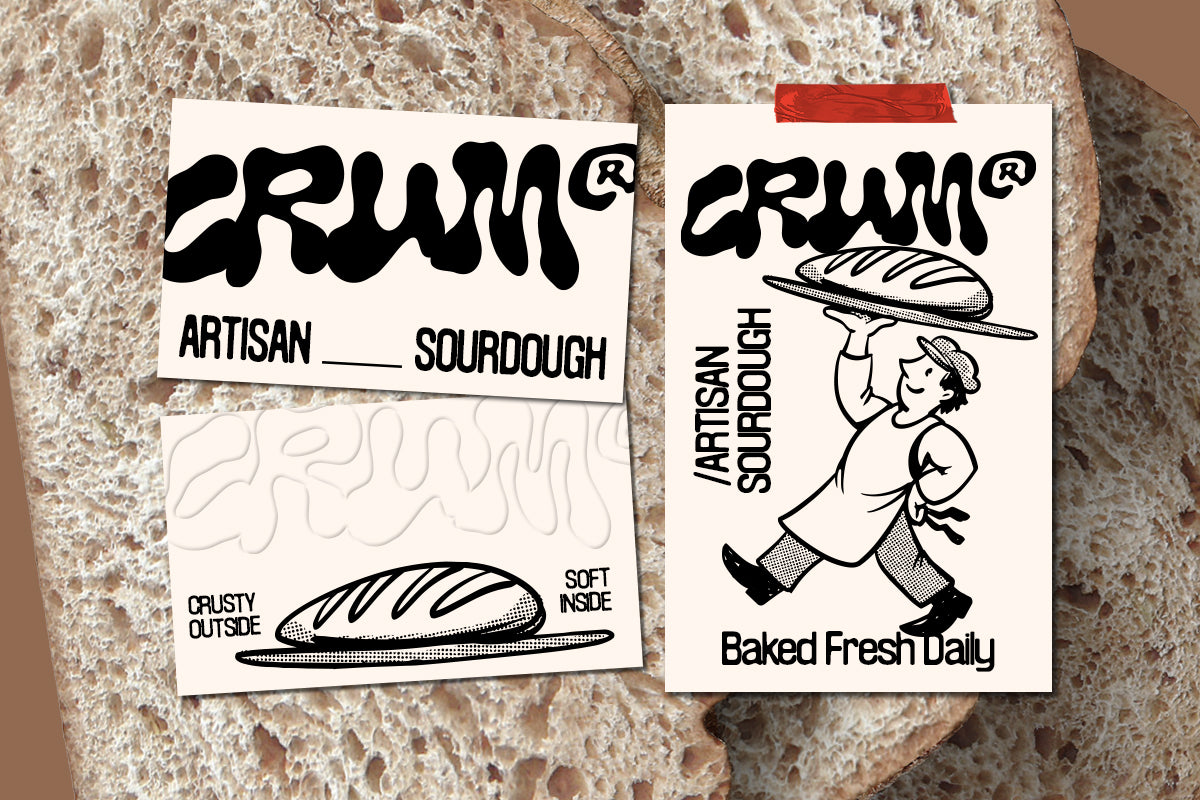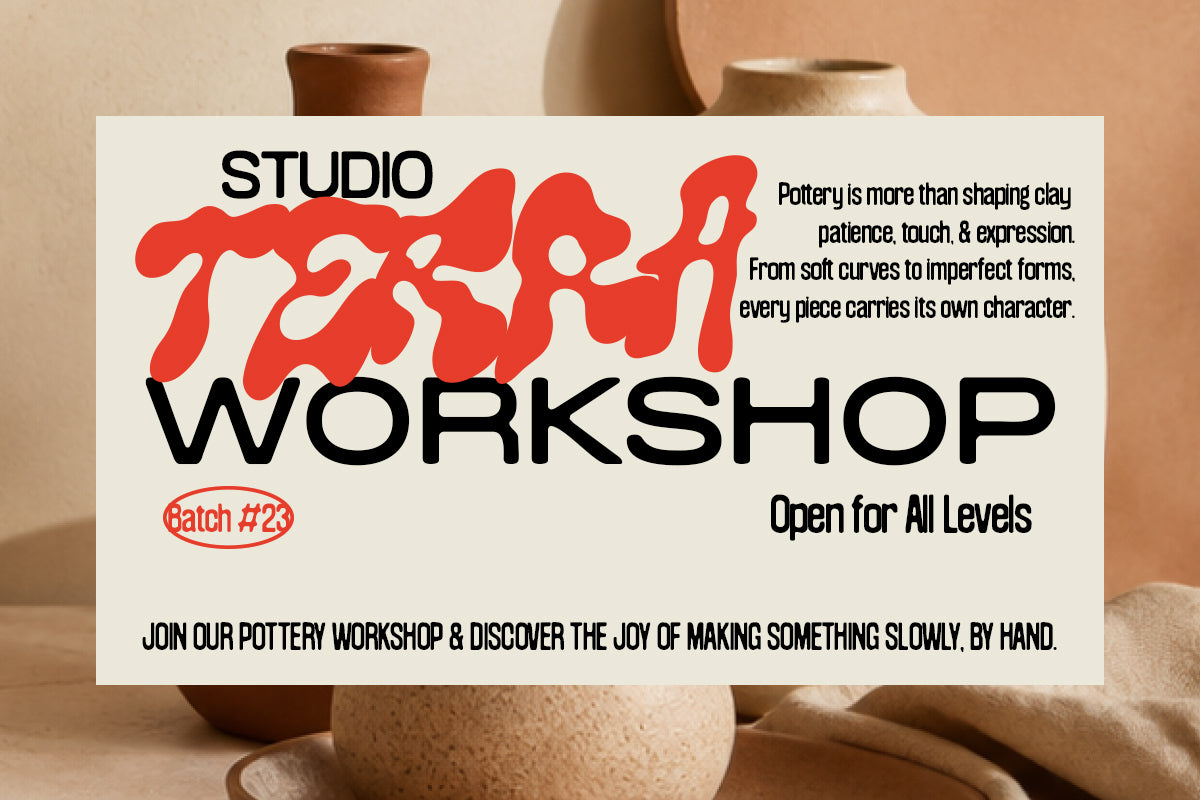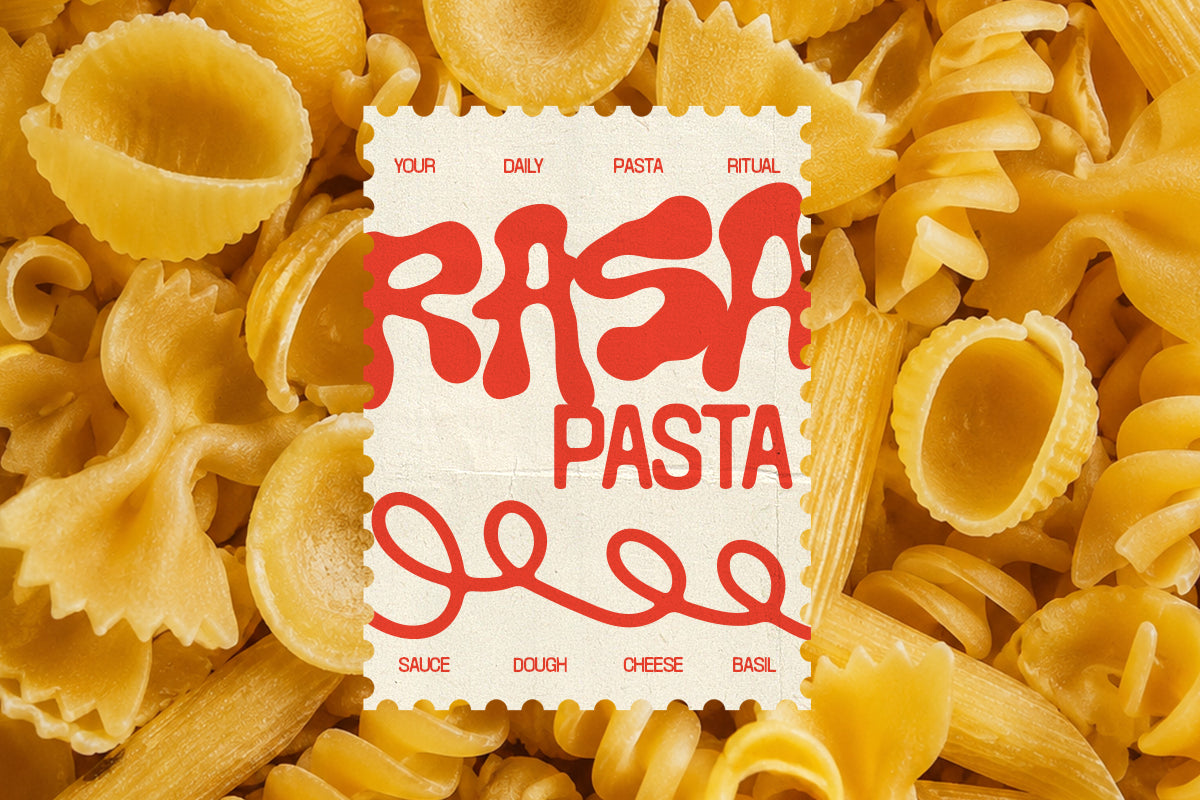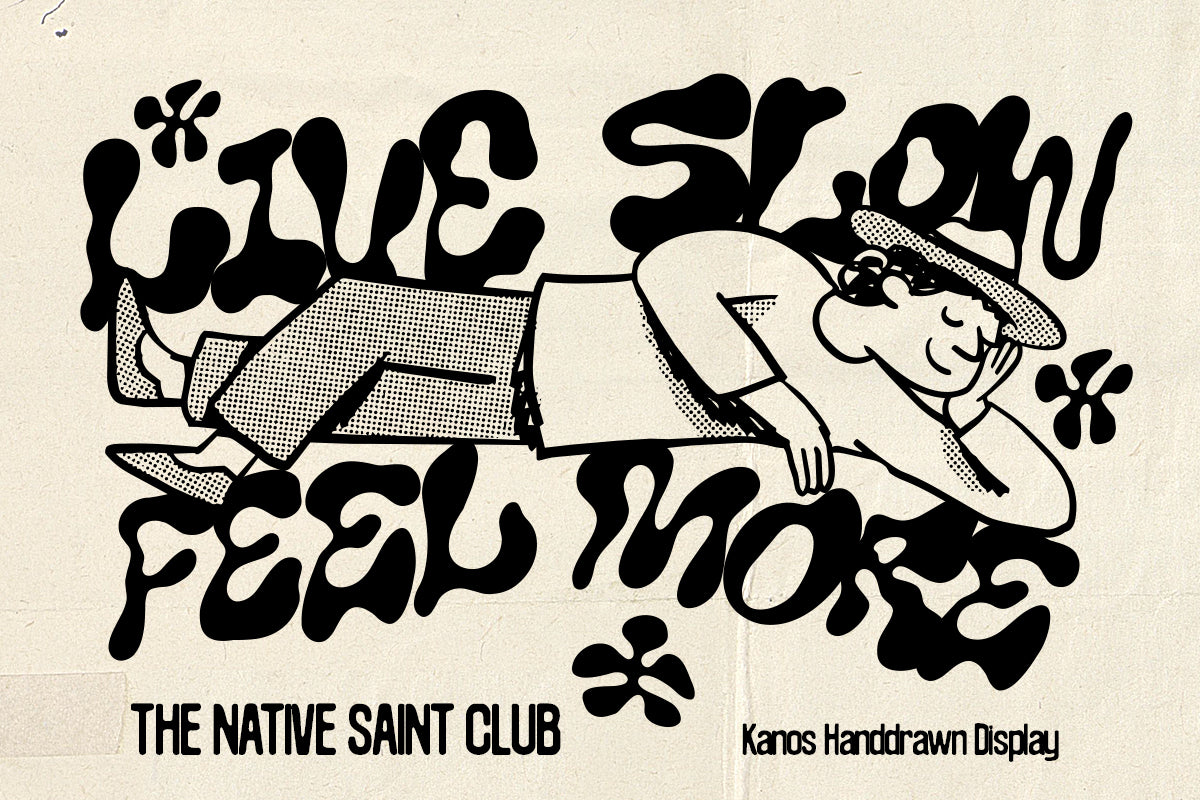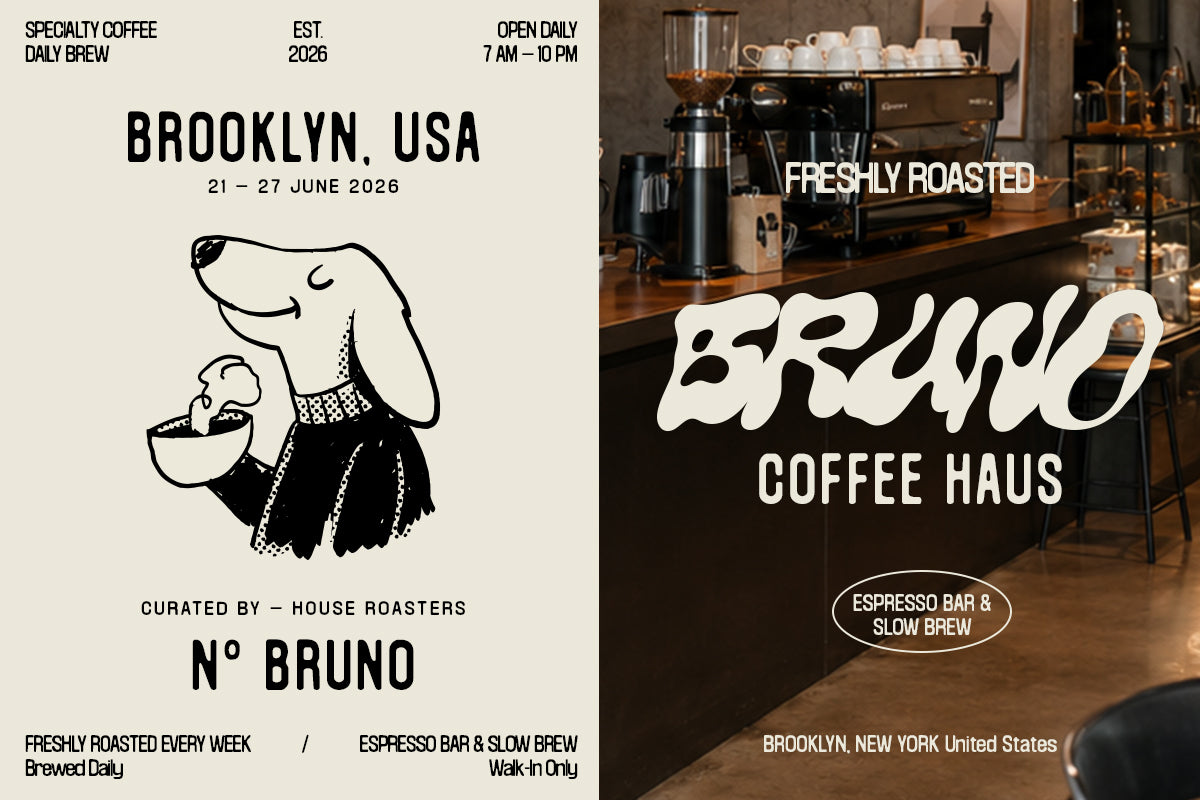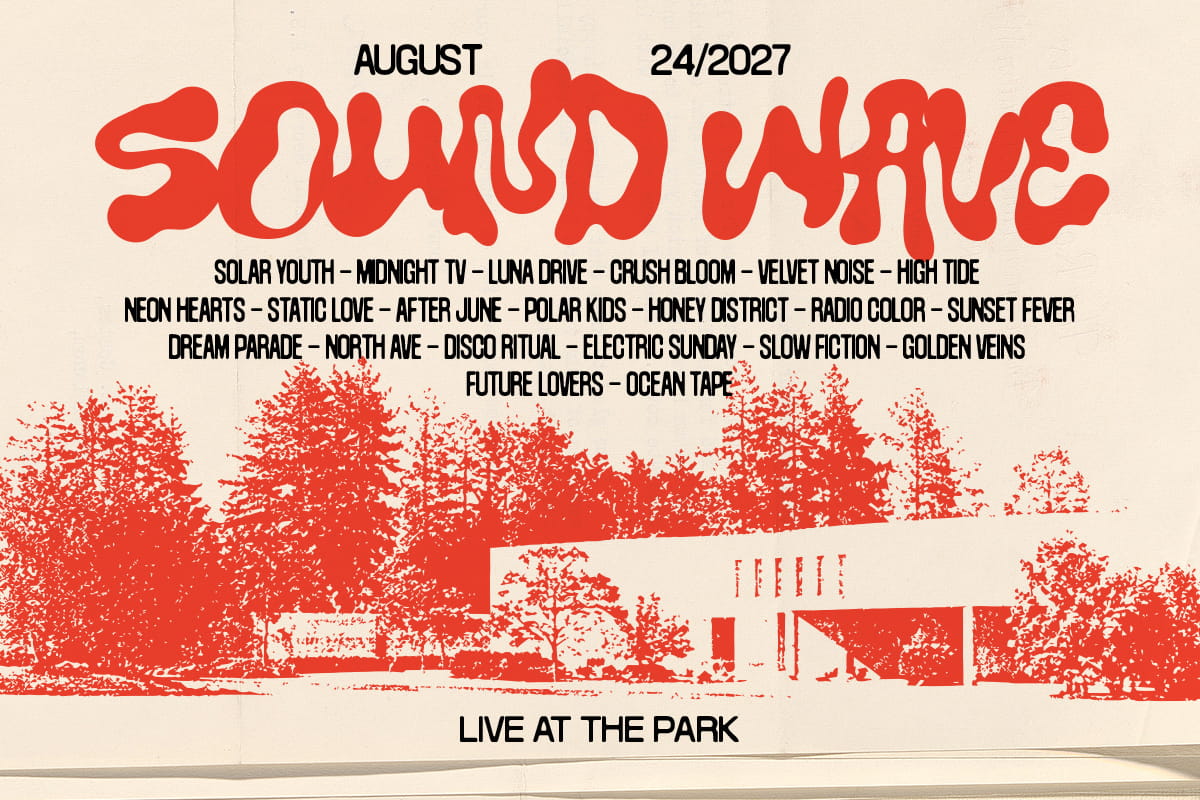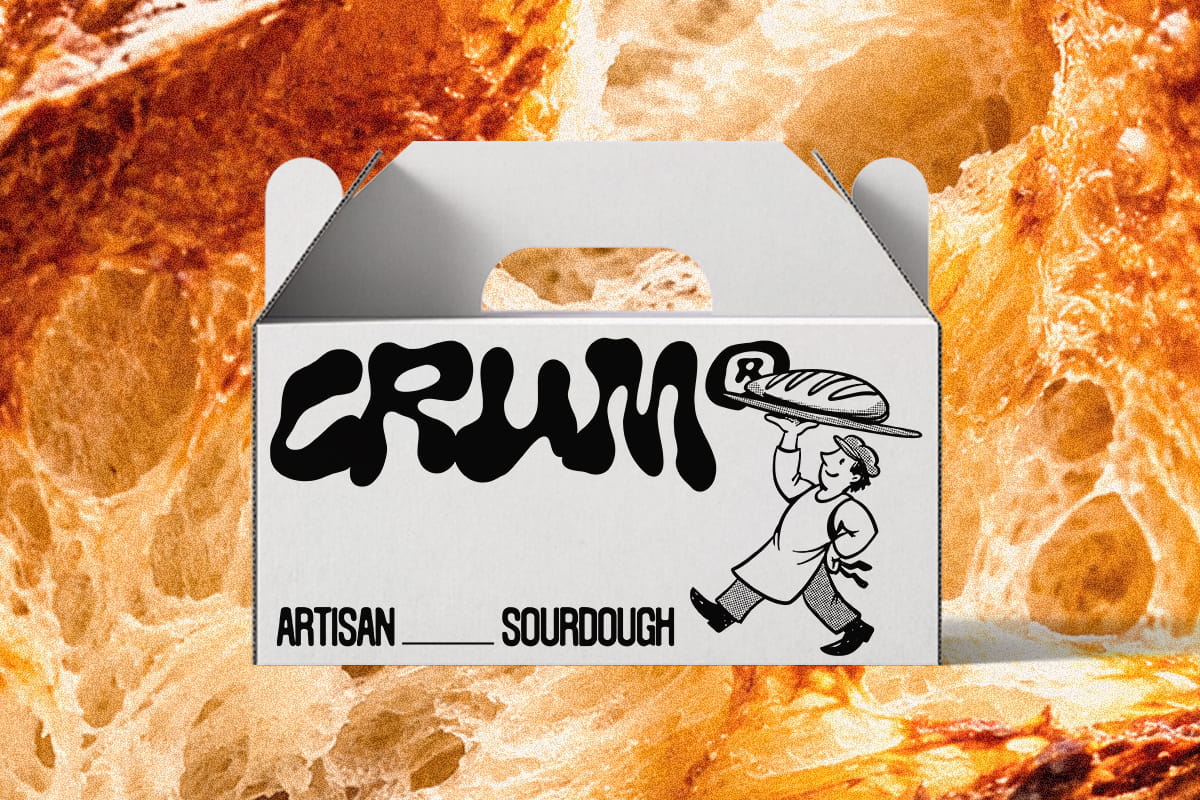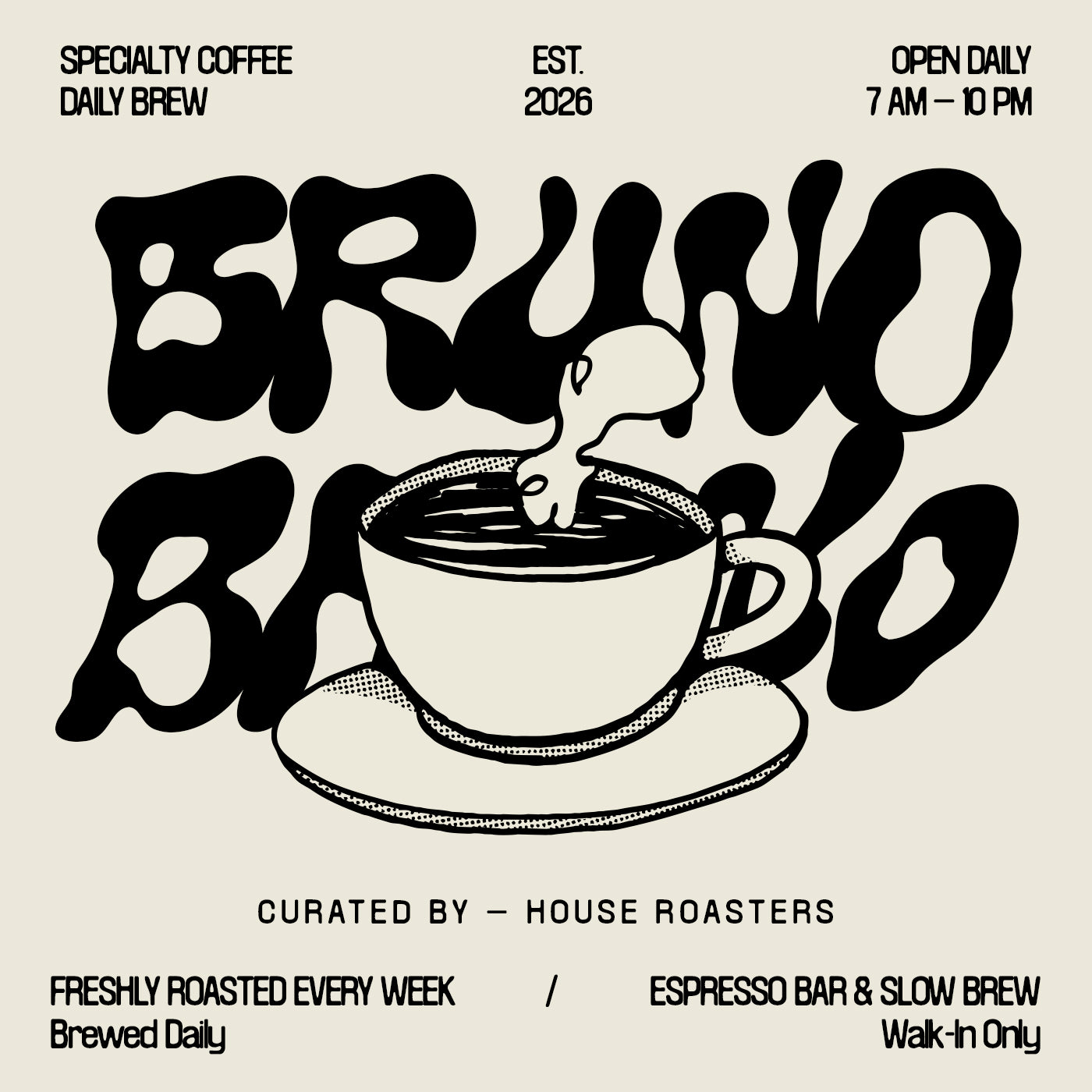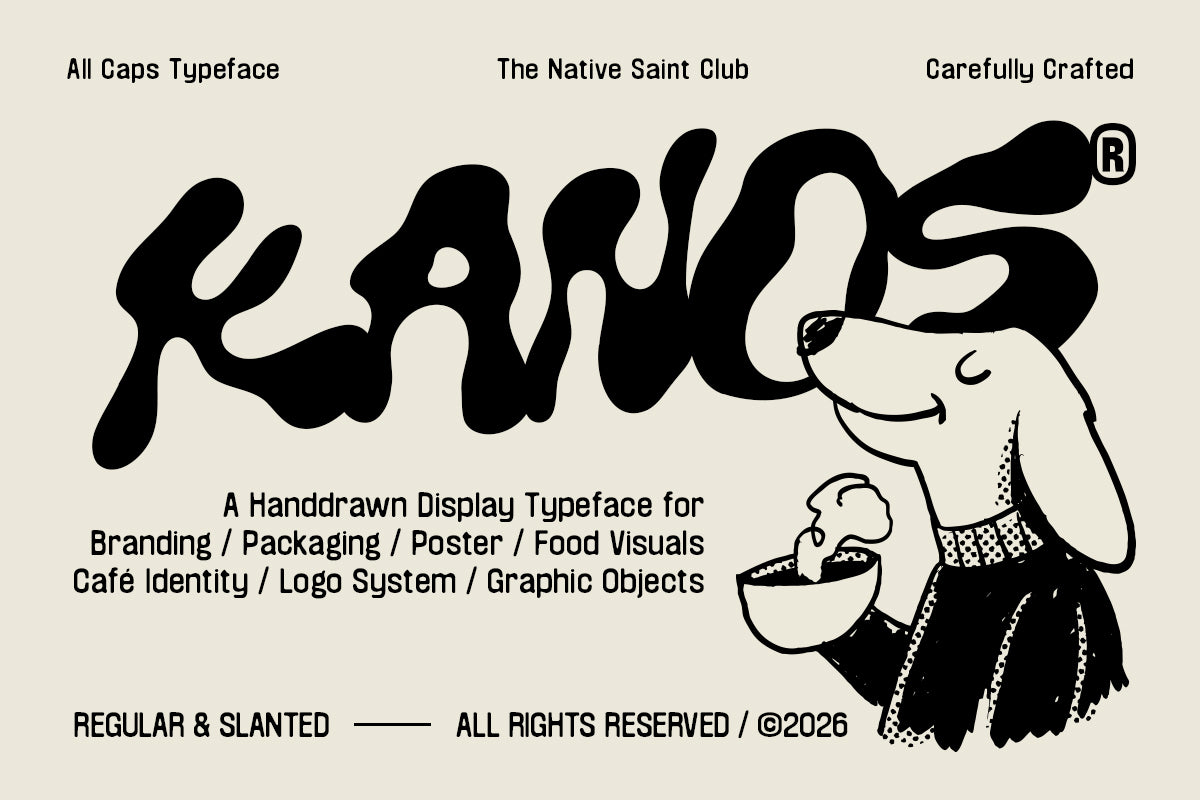
Tipografía Kanos TNSC
La tipografía Kanos funde cada letra en una mancha redondeada, similar a una burbuja, convirtiéndose en una tipografía de exhibición desenfadada y de aspecto dibujado a mano, con trazos gruesos y ensanchados y sin esquinas afiladas a la vista. El ligero temblor orgánico de cada curva hace que todas las palabras luzcan libres y entintadas a mano, en lugar de construidas sobre una cuadrícula.
Su variante inclinada lleva las mismas formas de letras burbujeantes hacia adelante para aportar un poco más de movimiento. Úsala para la identidad visual de cafeterías, etiquetas de embalaje, carteles de eventos y composiciones de logotipos divertidas.
Características
• 266 glifos
• 2 estilos (Regular, Slanted)
• 2 conjuntos estilísticos
• Mayúsculas
• Diacríticos
• Alternativas
• Números
• Puntuación
• Símbolos
• Divisas
• Matemáticas